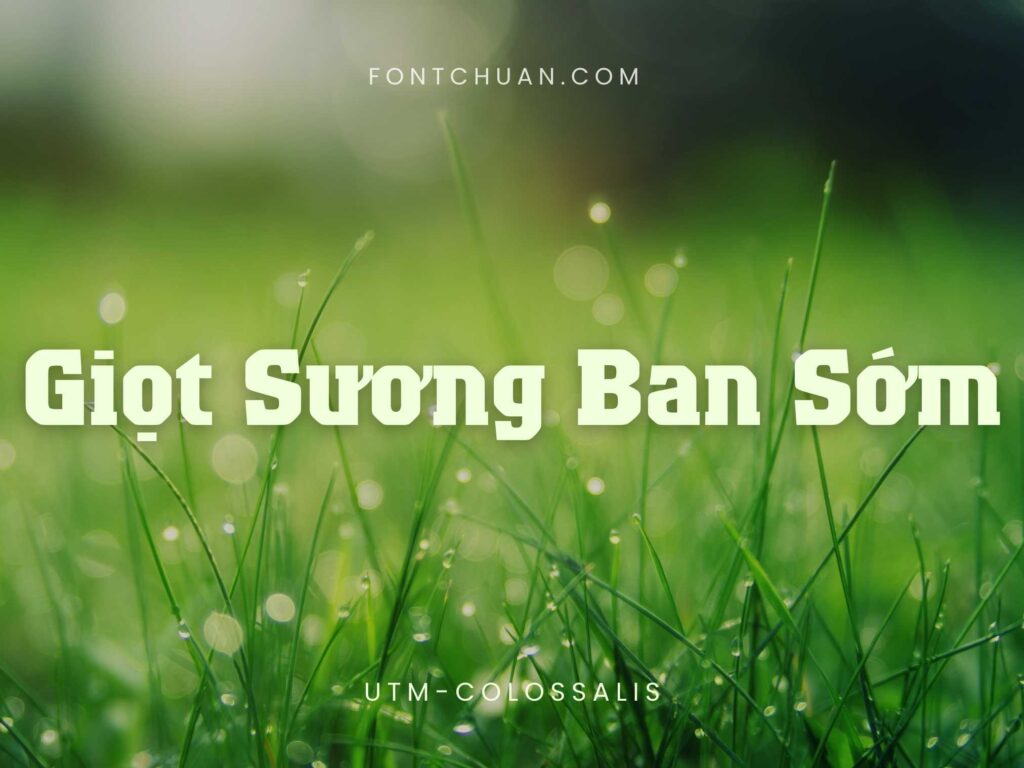
Font UTM Colossalis Việt Hóa là một kiểu chữ slab serif ấn tượng với các đường nét dày dặn, mạnh mẽ. Font gốc có tên là Colossalis, được thiết kế bởi Đang Cập Nhật. Đây là một lựa chọn hoàn hảo cho các tiêu đề, quảng cáo và các dự án thiết kế mang phong cách cổ điển hoặc hiện đại.
Font này đã được Việt hóa để hỗ trợ đầy đủ tiếng Việt bởi FontTiengViet, ngoài ra còn hỗ trợ hơn 200 ngôn ngữ khác. Thành viên của Font Chuẩn đã sưu tầm và chọn lọc font này nhằm đáp ứng nhu cầu của người dùng trong thiết kế và ứng dụng thực tế. Font có các ligatures đẹp mắt và phù hợp với các dự án như tiêu đề, quảng cáo, thiết kế poster, branding và nhiều lĩnh vực sáng tạo khác.